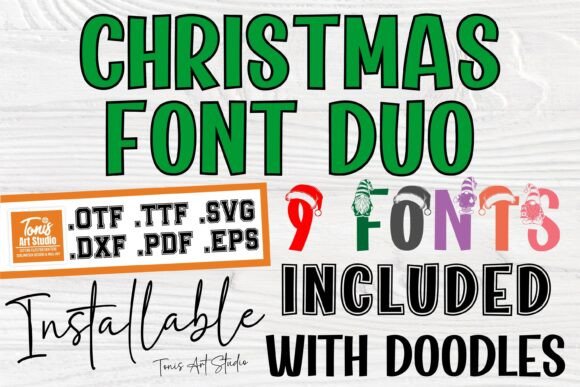
Christmas Duo Bundle
Ulasan Detalhada: Christmas Duo Bundle – O Pacote de Fontes Natalinas Definitivo
Se você procura dar vida ao espírito natalino nos seus projetos criativos, o Christmas Duo Bundle chega como a solução completa. Com 9 estilos de fontes exclusivos e uma coleção robusta de arquivos de corte, este bundle oferece tudo que designers, artesãos e entusiastas do Cricut ou Silhouette precisam para criar peças memoráveis nesta época festiva.
Principais Benefícios
- Variedade incomparável: 9 fontes diferentes – de Bold e Outline a versões temáticas como Gnomes e Santa Hat – garantem flexibilidade para cartões, convites, camisetas, canecas e muito mais.
- 🖋️ Fontes:
- Christmas Duo
- Christmas Bold
- Christmas Regular
- Christmas Italic
- Christmas Line
- Christmas Outline
- Christmas Gnomes
- Christmas Santa Hat
- Gnomes Doodles
Para quem é indicado?
Este bundle é perfeito para:
- Designers gráficos que criam convites, cartões e flyers natalinos.
- Artesãos de impressão e corte que produzem adesivos, decals para carro, e decorações de parede.
- Empreendedores de merch — camisetas, canecas, almofadas e produtos personalizados.
- Professores e organizadores de festas que precisam de material visual rápido e festivo.
Porque escolher o Christmas Duo Bundle?
Além da qualidade tipográfica, o bundle entrega versatilidade total graças aos arquivos vetoriais. Isso significa que você pode redimensionar sem perder nitidez, adaptar cores e combinar estilos em um único projeto. A presença dos temas “Gnomes” e “Santa Hat” acrescenta um toque divertido que diferencia suas criações das típicas fontes de Natal.